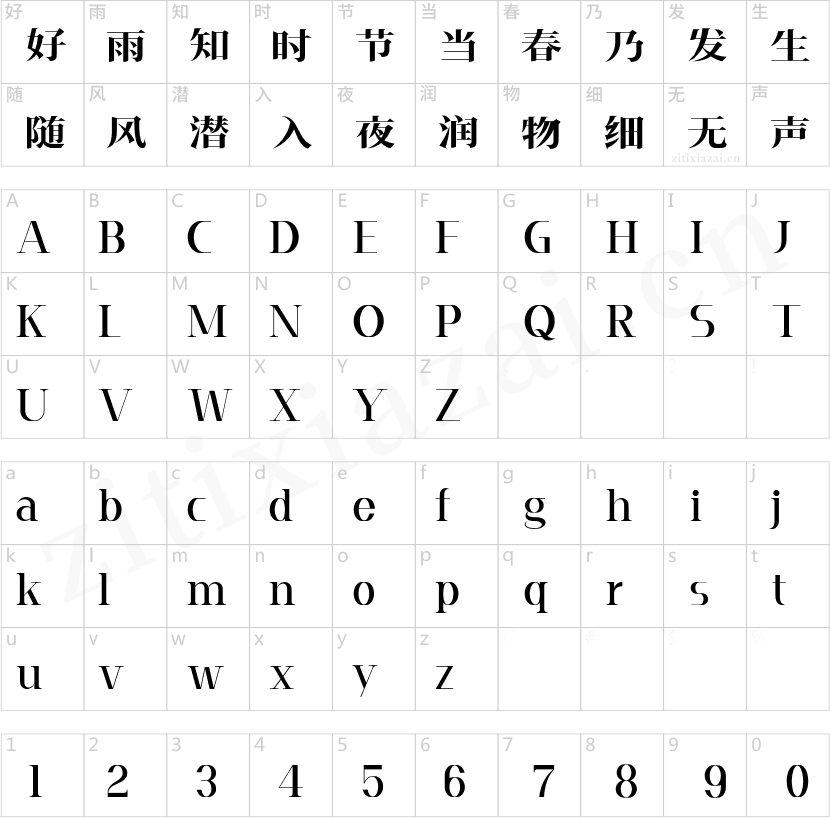
字魂独角兽体
字魂独角兽体,这款字体结构工整、笔画清晰,兼顾美观与易读性,适用于标题、正文、海报、包装、LOGO 等多种场景。字形优雅稳定,风格百搭耐看,适配日常排版与创意设计,让文字呈现更舒适、更具质感。字魂独角兽体一笔一画,皆是细节,以均衡的比例、流畅的线条打造舒适视觉体验,字形端正大气,风格简约现代。无论是商业设计、品牌宣传还是日常排版,都能轻松驾驭,让文字更有格调与力量。字魂独角兽体字体下载。